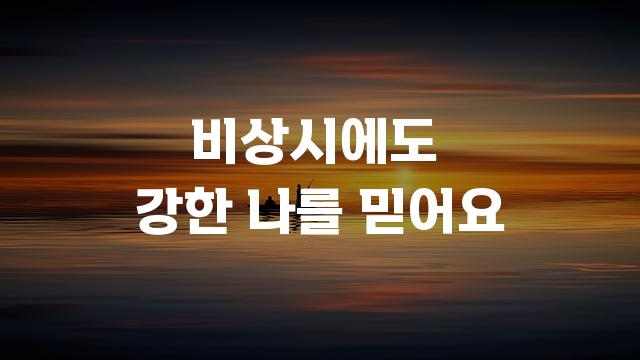
바른공군체는 대한민국 공군과 투게더그룹이 제작한 기본 고딕 스타일의 폰트로, 꽉 찬 느낌의 글자가 특징입니다. 이 폰트는 현대적이면서도 단단한 인상을 주어 다양한 디자인에 활용하기 좋습니다.
바른공군체은(는)
기본 고딕, 굵은 고딕, 감성적인, 단단함, 부드러움 계열의 생김새를 가지고 있으며
프레젠테이션, 보고서/문서, 출판물 제목 등에서 자주 활용되며, 효과적인 메시지 전달에 적합합니다.
이 폰트는 기술/IT, 공공/정부, 금융/비즈니스 분야에 잘 어울리며,
신뢰감, 명확한, 전문적인 느낌을 담고 있는 것이 특징입니다.